あるあるタイポ。誰でもできる文字加工のデザイン集
人気書籍あるあるデザインシリーズ最新作「あるあるタイポ。」が登場。
今回は「タイポグラフィ」「作字」をテーマに、そのグラフィカルな文字の特徴をワンフレーズで言語化し、わかりやすく届けられる。
「あるあるタイポ。誰でもできる文字加工のデザイン集」では、文字加工された「タイポグラフィ」や「作字」が、どのように「ポスター」や「バナー」などのデザイン制作物に活かせるのかがわかりやすいように、デザイン作例をたくさん紹介している。
既存のフォントではインパクトを出せないとき、良い画像やビジュアル素材がないとき、文字を加工するだけでキャッチーなデザインを作れたら、。
重ねたり、ぼかしたり、書体をミックスさせたり、切断したり……! さまざまな手法を駆使したデザインを紹介する。
「ゆる極太」「均一に攻めて」など、文字の特徴を捉えた言葉とビジュアルを一緒にインプットして頂き、文字加工の引き出しを増やしていこう。
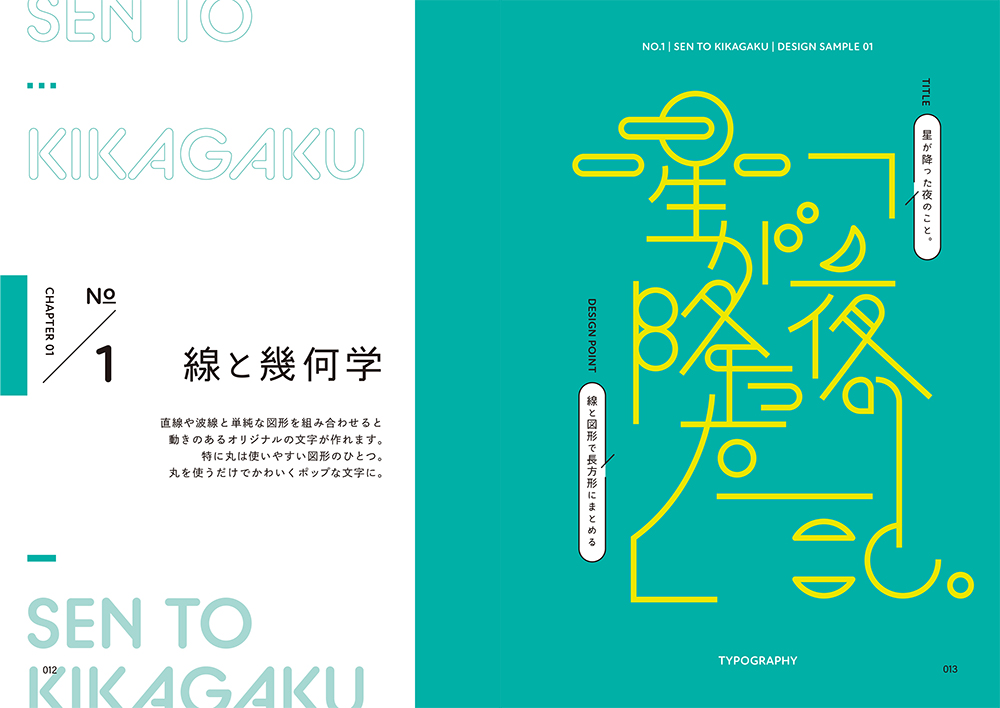
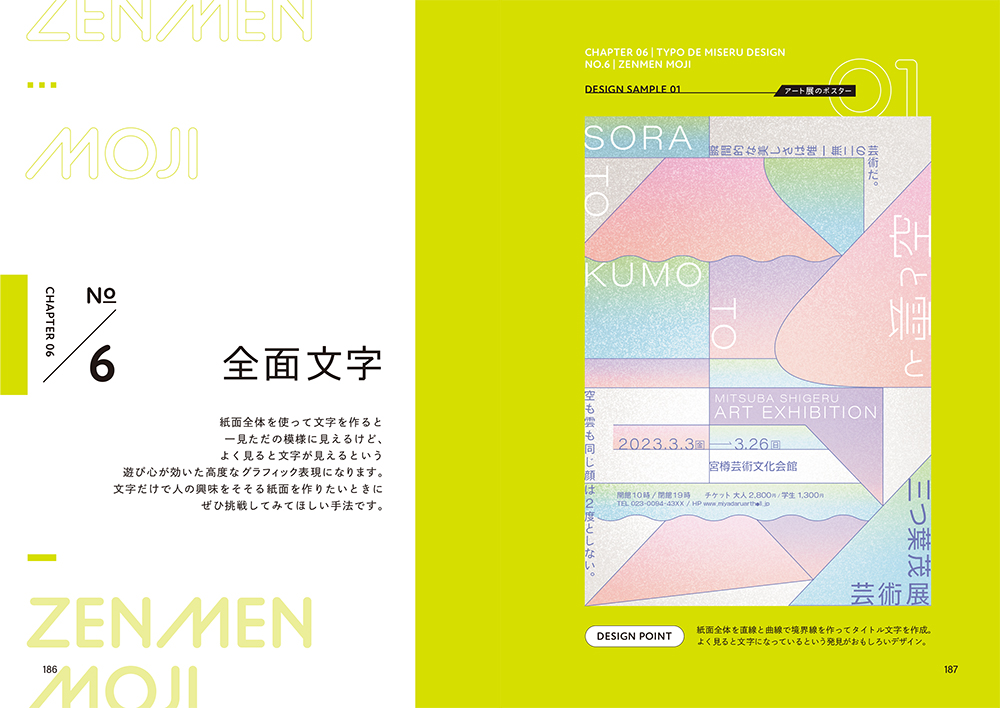
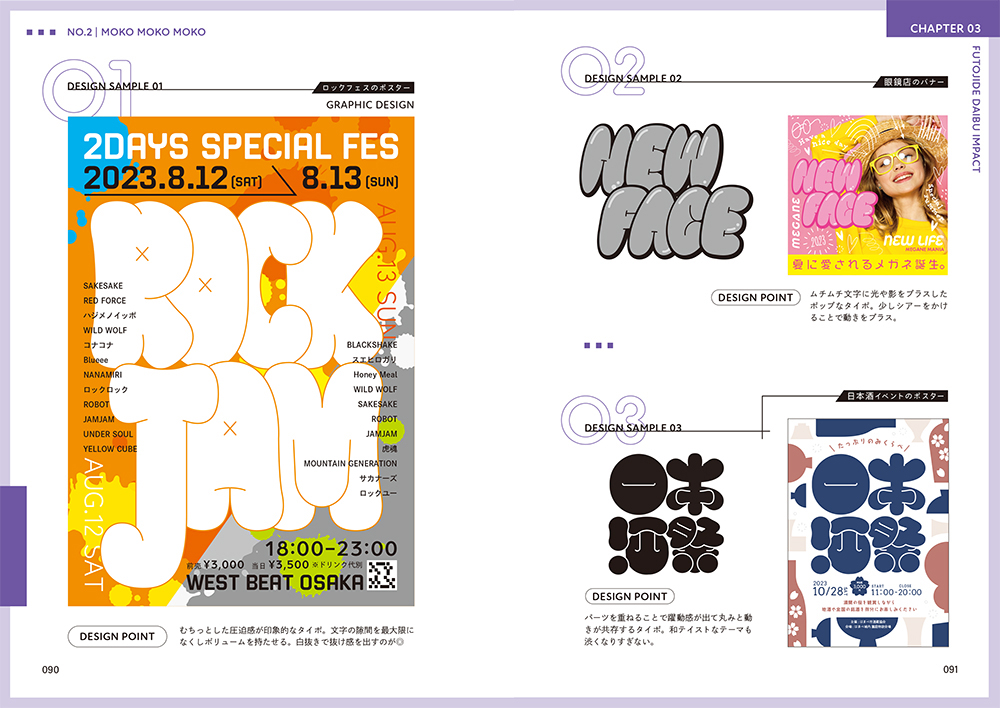
「あるあるタイポ。誰でもできる文字加工のデザイン集」のおもな内容
●Chapter01 線で見せるタイポ。
線と幾何学/かよわかぼそく/なめらか手書き
●Chapter02 グッと読ませるタイポ。
つなげて言葉を/明朝体アレンジ/文字の中をぬりぬり
●Chapter03 太字でだいぶインパクト。
太め角丸ポップ/もこもこもこ/ゆる極太
●Chapter04 飛び出して立体感。
重ねて飛び出し/影をベタ塗り/影だけにカラー
●Chapter05 アートなタイポ。
イラスト混ぜ込み/切り絵の風合い/スプレーアート
●Chapter06 タイポで見せるデザイン。
書体M I X/バラバラ切断書体/書体で埋めすぎ
...ほか